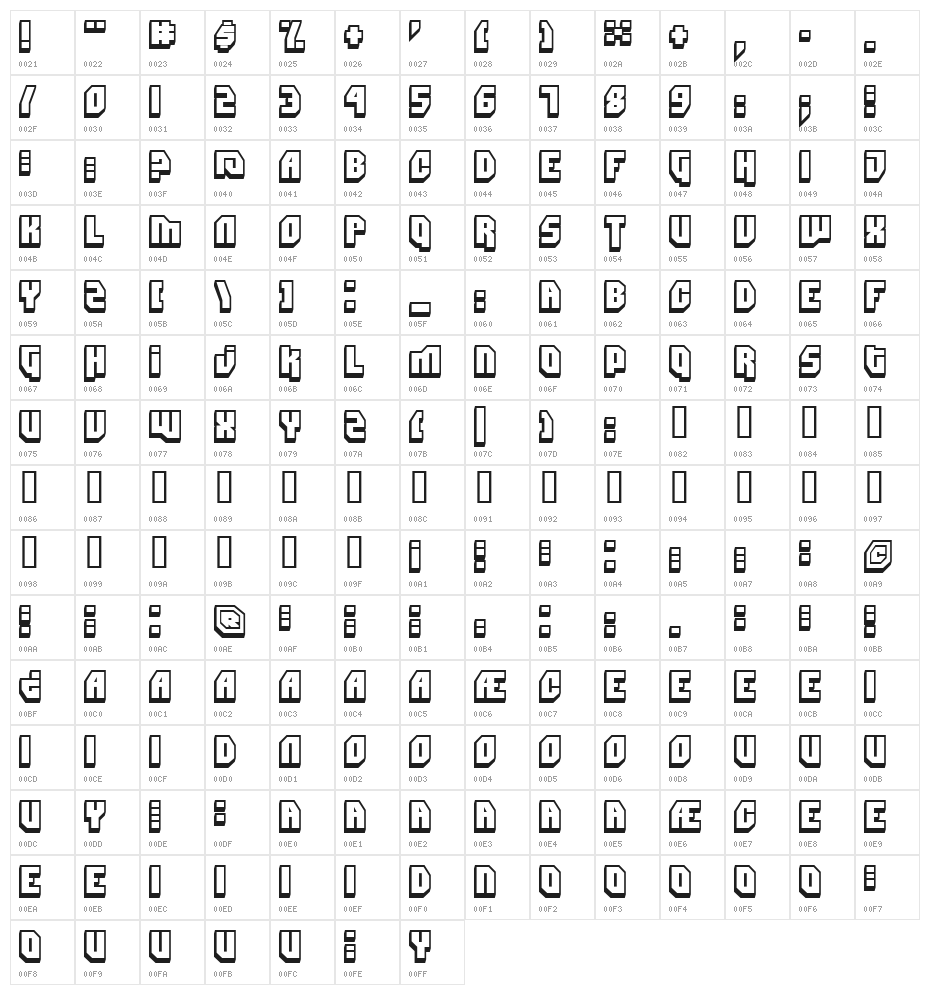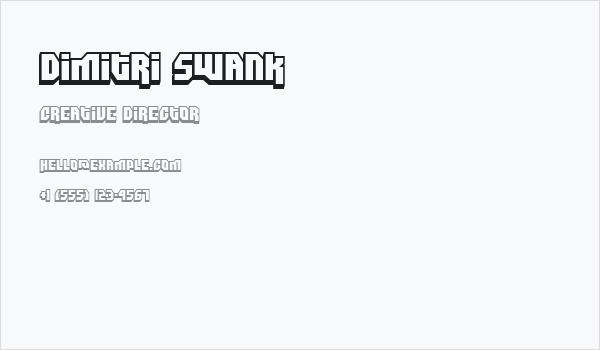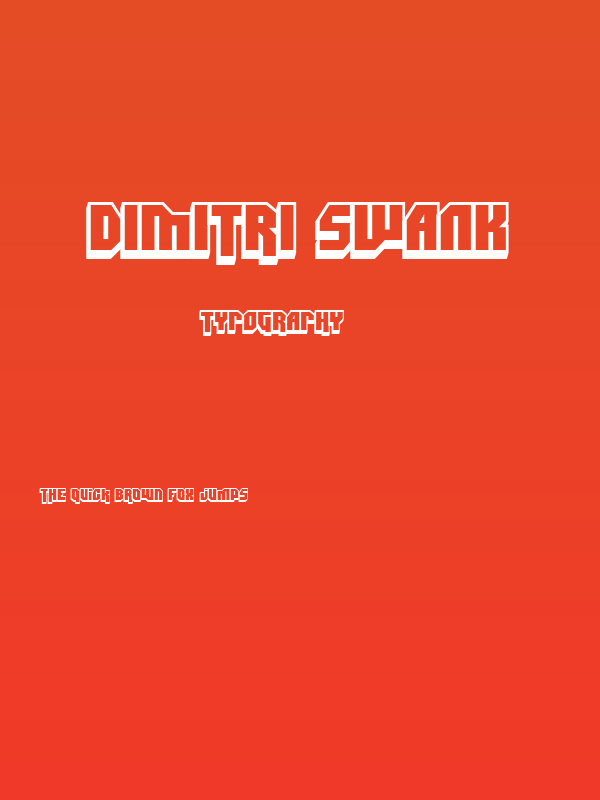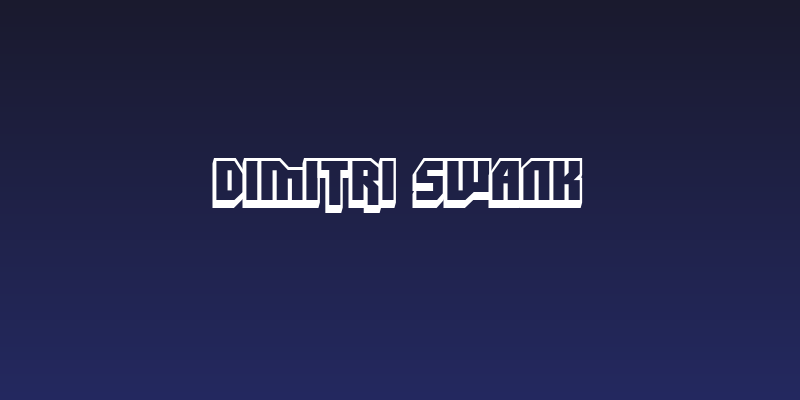
Dimitri Swank Font
| श्रेणियाँ | Outline |
| कंट्रास्ट | High |
| उपयोग का मामला | Headlines, Logos |
| सुझाए गए प्रोजेक्ट | Perfect for video game titles, posters, logos, and any project requiring a futuristic or tech-inspired aesthetic. |